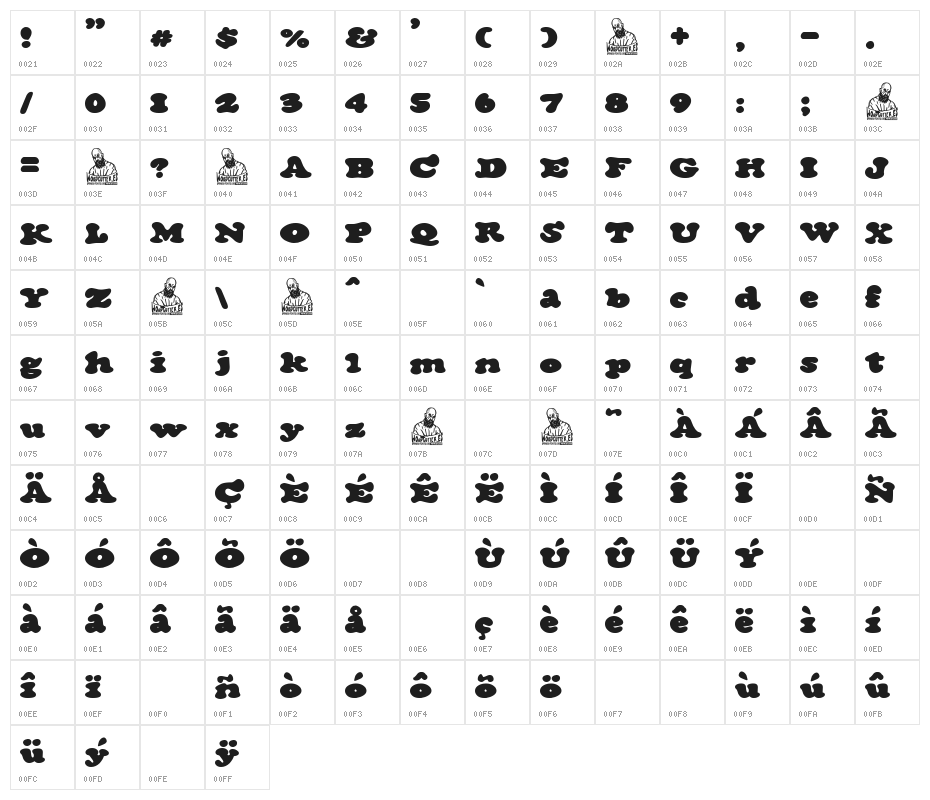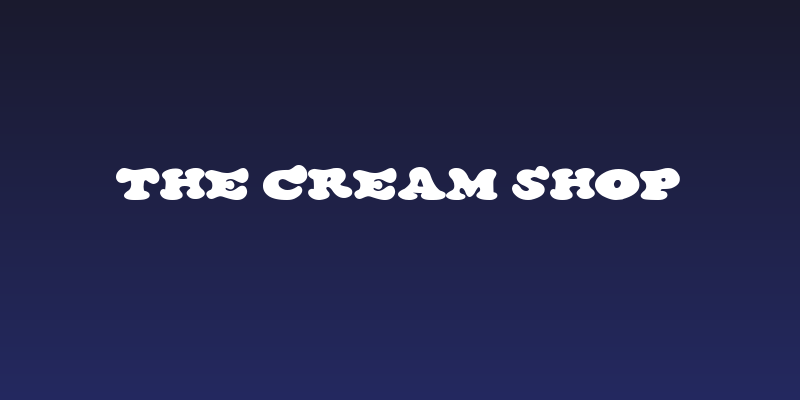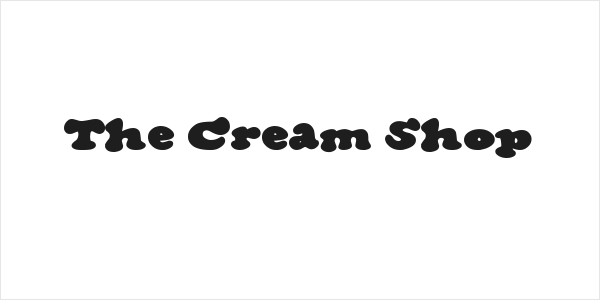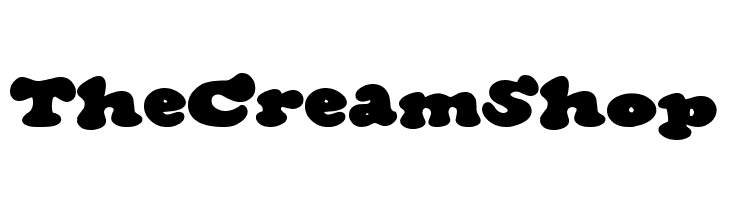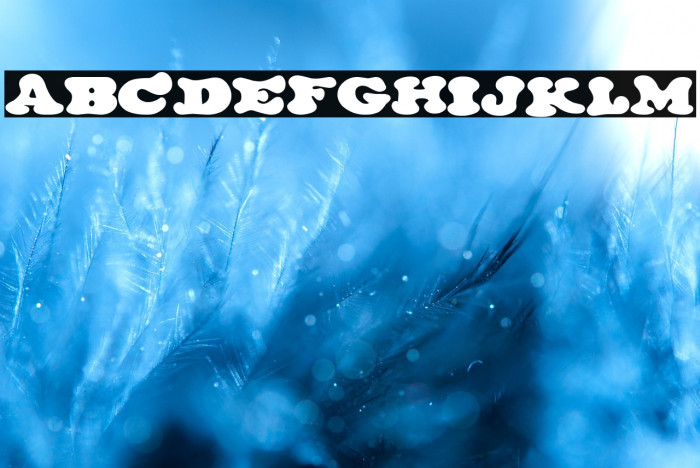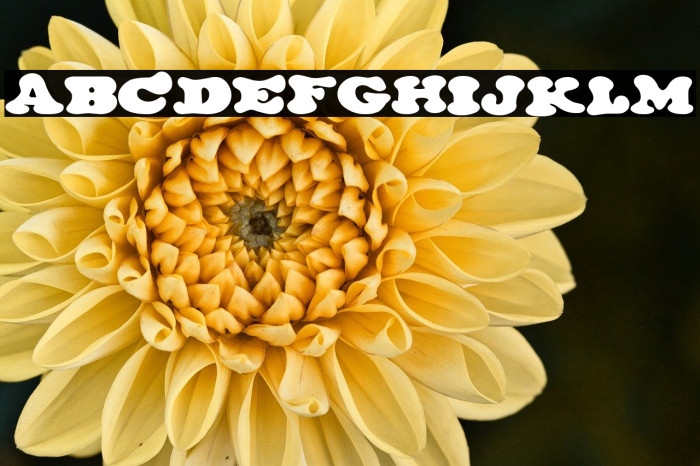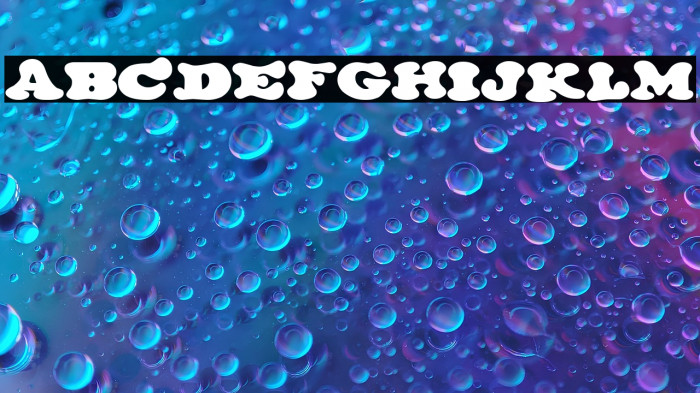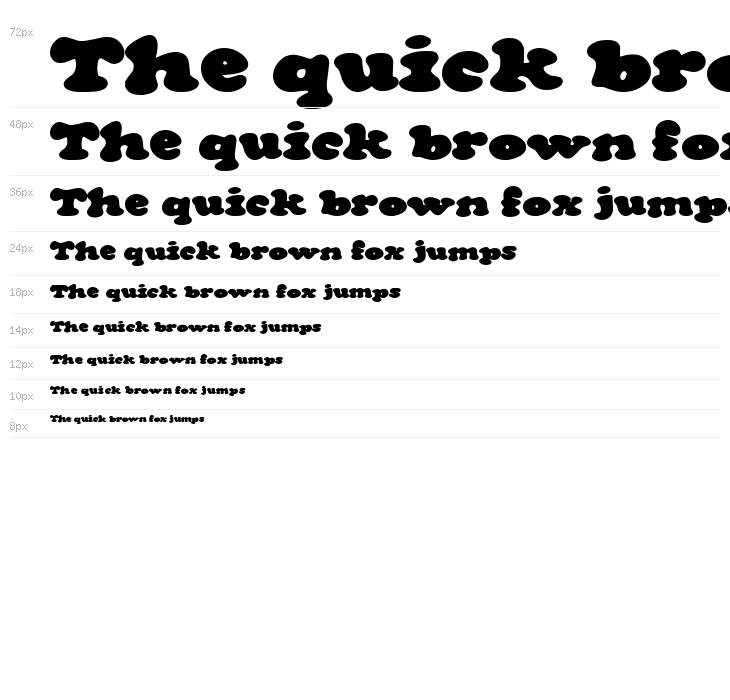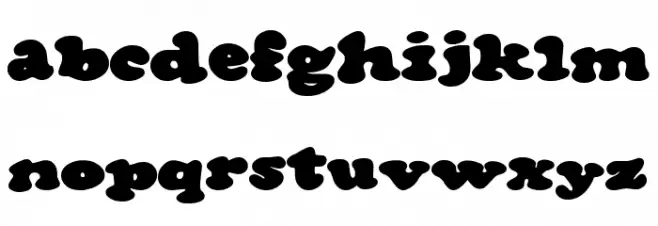
The Cream Shop Font
| Gesamtstil | Playful, Whimsical, Cartoonish |
| Anwendungsfall | Headlines, Logos, Creative Designs |
| Vorgeschlagene Projekte | Ideal for children's books, playful branding, eye-catching headlines, and creative designs. |